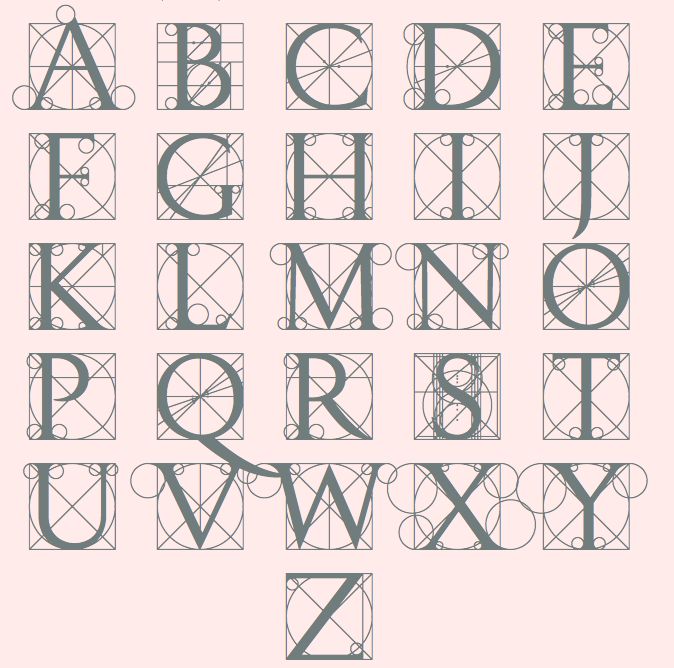
ТАБЛИЦА 24
ЛАТИНСКИЙ АЛФАВИТ ПО МАТЕРИАЛАМ
КОЛОННЫ ТРАЯНА * В РИМЕ.
МЕТОД ЭРНСТА ДЖОНСОНА
Классический латинский шрифт точно воспроизведен в 1936 году
О. Джонсоном по надписям, сделанным на памятнике римской
архитектуры — колонне Траяна, построенной в I веке н. э. архитекто¬
ром Аполлодором.
Шрифт надписей колонны Траяна в Риме считается наиболее за¬
кономерным из всех классических шрифтов на памятниках латинской
письменности. Им пользовались как образцом Л. Поччиоли, А. Дю¬
рер, т. Іори и другие мастера эпохи Возрождения при создании
своих шрифтов. Шрифт колонны Траяна является основой современ¬
ных латинских шрифтов, так называемой антиквы.
Э. Джонсон установил метрические закономерности шрифта колон¬
ны Іраяна и дал его точное графическое построение на основе мо¬
дульных отношении.
Буквы N. К, V, У, Z, отсутствующие в тексте надписи на колон¬
не, построены Джонсоном на основе закономерностей, выявленных при
Шрифт отличается красотой, легкостью и вместе с тем фунда¬
ментальностью. Форма букв и пропорции их элементов определялись
необходимостью воспроизведения надписей на камне. В связи с этим
в буквах нет тонких, так называемых «волосных» элементов, которые
например,в имеют место в других шрифтах (см. табл. 10, 12, 15, 16,
Основной единицей метрического анализа является высота букв
Ѵна принята за модуль и разделена на 10 частей—парт. Ширина
/Г/Ш аеКЯ В широких пределах —от 0,3 модуля до 1,05 модуля
чающего построение букв, принято 0,78 модуля.
лавные прямые и криволинейные элементы имеют ширину, рав¬
ную в средней части 0,08 модуля Другие элементы имеют ширину в
модуляJ. К последним относятся все горизонтальные элементы.
Ларактернои особенностью шрифта, определяющей его стройность
и устойчивость, является уширение прямых элементов к концам, на¬
чиная с четверти высоты.
Начало уширения отмечено в таблице
утолщенной горизонтальной чертой. Элементы уширяются на конце
на U.U1 модуля в каждую сторону, так что основной элемент по кон¬
цам имеет ширину 0,1 модуля.
Подсечки сопрягаются дугами радиусом 0,06 модуля. Общая
М *Се«ПОСТРОеНИЯ ХОрОШО вндны І1а чертеже. Размеры главных эле¬
ментов букв указаны в долях модуля (высоты). Размеры других эле-
В* тМаблУТ iqITb Лег,
табл- 19 представлен русский алфавит, построенный на
основе рассматриваемого шрифта. В „ем строго сохранены все особен¬
ности латинского шрифта и на их основе построен ряд новых букв
ТраянаДУ£Т °™еТИТЬ °СОбеННОСТИ постРоения шрифта колоты
В буквах В, Р, R горизонтальные участки окоѵглых
примыкающие к вертикальным стойкам, имеют разную толщину
(верхний —большую), вследствие чего центры наружного и внутрен¬
— ? буквах О и Q наружные и внутренние контуры представляют
“ чет,ьірех«ентр°вые овалы с наклоненной влево большой
СЬЮ.
6 высоты. ’
Шрифту посвящен небольшой отрывок из третьей книги «Наставления к измерению циркулем и линейкой линий, плоскостей и объемных тел, составленного Альбрехтом Дюрером и напечатанного, с относящимися к сему рисунками, на пользу всем любителям искусства в 1525 году» («Underweysung der Messung, mit dem Zirckel und Richtscheyt, in Linien, Ebenen unnd gantzen corporen…»). Книга целиком на русский язык не переводилась. Отрывок о шрифте выходил в трех редакциях (четырех изданиях):
- Построение шрифта Дюрера // Писаревский Д. А. Шрифты и их построение / под ред. И. А. Фомина. Л.: Издание автора, 1927. С. 52—56.
- Построение шрифта Дюрера // Писаревский Д. А. Шрифты и их построение / под ред. И. А. Фомина. М.: Архитектура-С, 2014. С. 52—56.
- Из книги III [трактата «Руководство к измерению»] // Дюрер А. Дневники. Письма. Трактаты / пер. Ц. Г. Нессельштраус. Л.; М.: Искусство, 1957. Т. II. С. 68—73.
- Дюрер А. О шрифте / пер. В. Лазурского. М.: Книга, 1981.
Целиком отрывок о шрифте переведен только в третьем издании 1981 года. Здесь приводится текст первого издания. Перевела фрагмент Александра Николаевна Фомина. Для контроля также приводится электронное факсимиле издания: duerer_postroenie-shrifta_1927.djvu.
Д. А. ПИСАРЕВСКИЙ
ПОД РЕДАКЦИЕЙ
ПОСТРОЕНИЕ ШРИФТА ДЮРЕРА
(перевод с немецкого А. Н. Фоминой *).
Часто приходится делать шрифт на столбах, башнях и высоких стенах, поэтому, кто хочет писать на башне так, чтобы верхнюю строчку букв можно было бы прочесть так же легко, как и нижнюю, тот должен сделать ее наверху крупнее, чем внизу, следующим образом: поставь свое лицо на таком расстоянии от башни и на такой высоте, как ты хочешь.